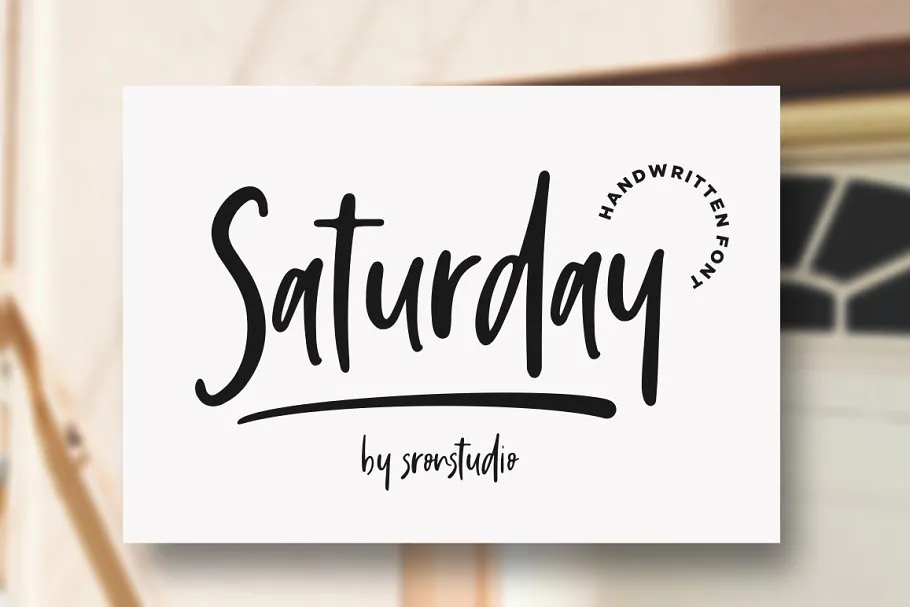
A C00zona nos apresenta a Saturday Vibes Script Font — uma nova abordagem para as fontes de script frescas e autênticas. Este é mais do que apenas uma font: ele é um design criado com amor, destinado a dar vida às suas melhores ideias gráficas. Introduzida pela Sronstudio, Saturday Vibes se destaca por sua naturalidade moderna. Ideal para diversas aplicações, esta font pode ser usada em desde logotipos e identidades de marca até embalagens de produtos e design de eventos especiais. Seja você um designer ou criador de conteúdo, o Saturday Vibes Script é perfeito para inovar e dar vida a suas criações. Suas opções modernas e atuais são certeza de sucesso em qualquer projeto que você escolha usar esta font. Desde as etiquetas até as postagens nas redes sociais, este é um recurso gráfico que merece uma olhada!